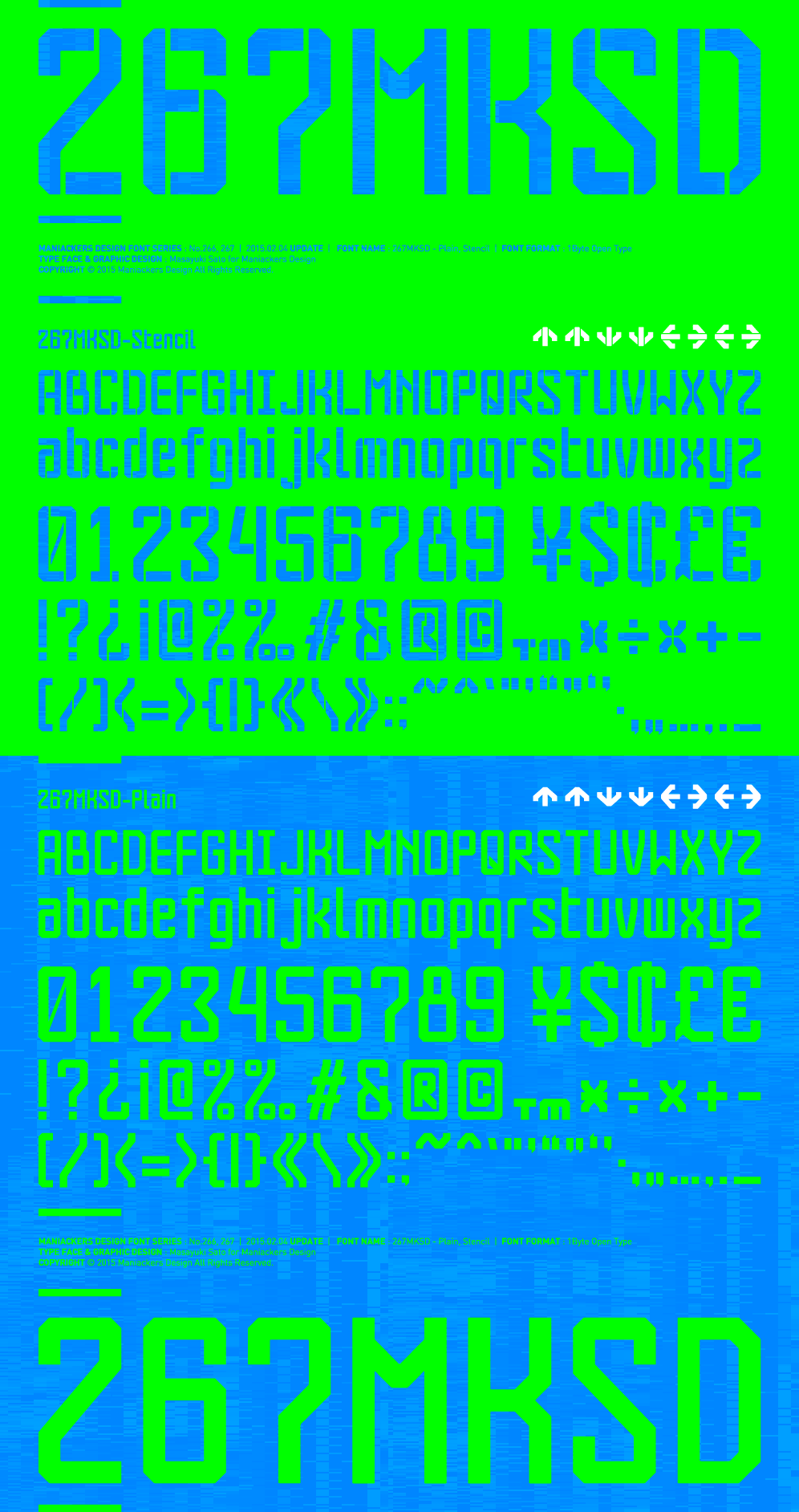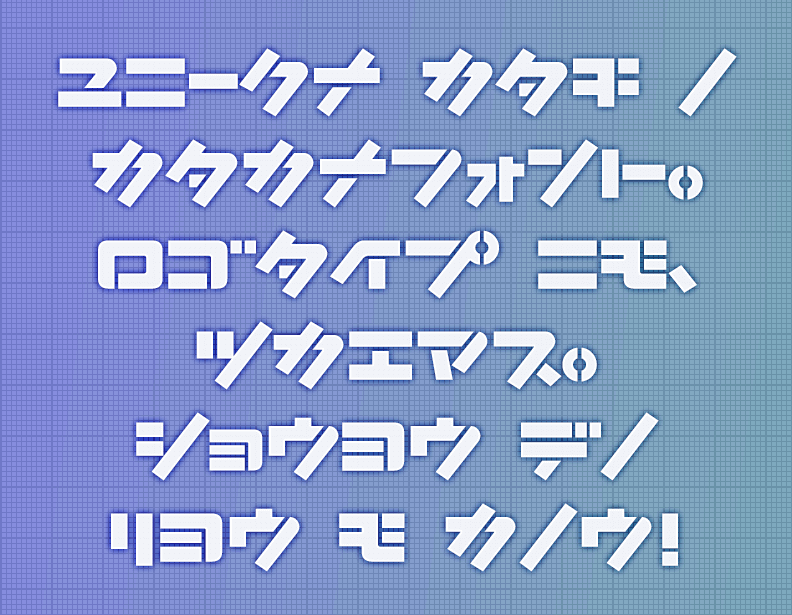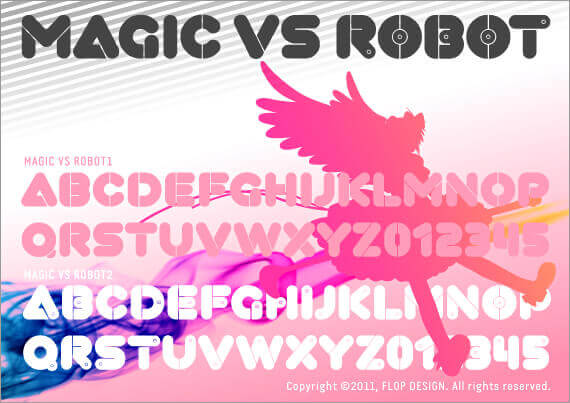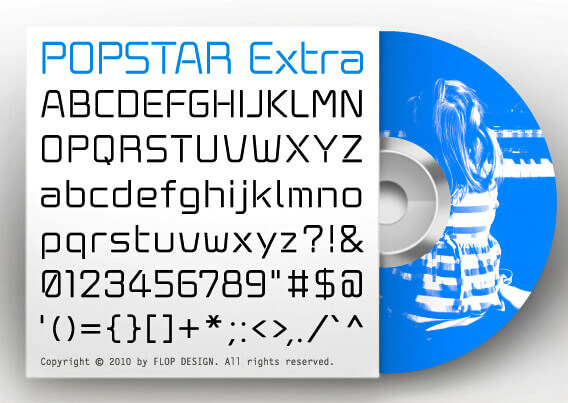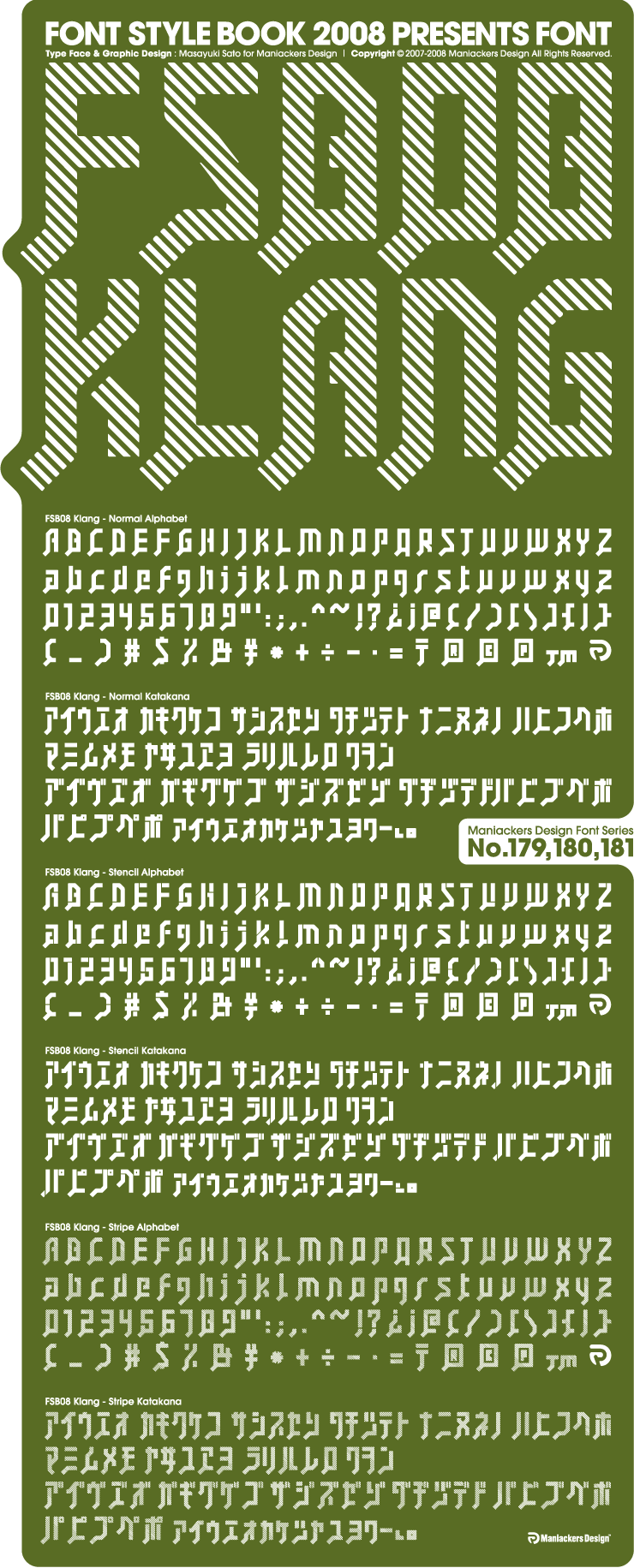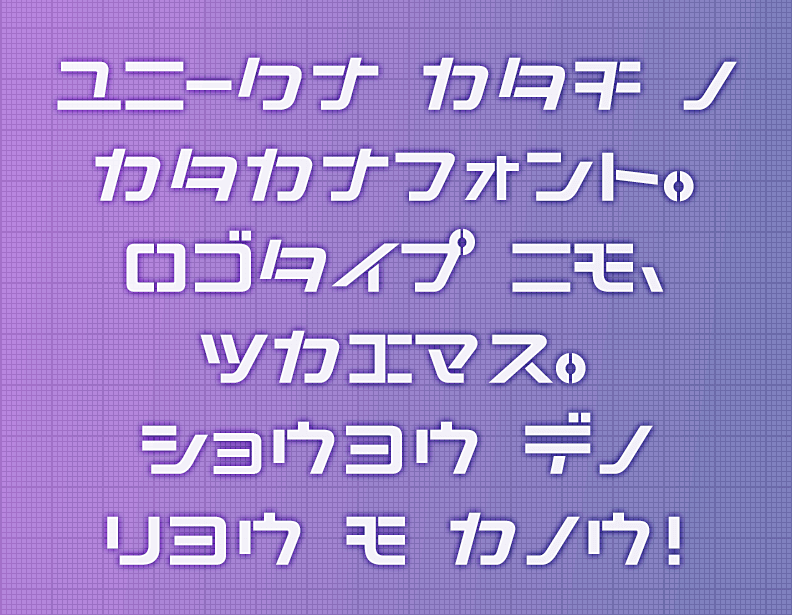
239 Schablone-AL
ステンシルタイプのエクステンド(文字の横幅を広げた)なテクノ系フォント。
267MKSD – Plain, Stencil
Plain(プレーン)とStencil(ステンシル)の2ファミリーが用意されているフォント。
268MKSD Fishhook – Light
「釣り針」のような造形をしたライトな欧文フォント。
Cardia Bold
斜体のステンシル系フォントの太字版。
FSB08 Klang-AL, KT
建築事務所「KLANG」のロゴタイプデザインから派生されたフォント。
Subway
地下鉄をモチーフにした、ちょっとレトロなフォント。
TM Extended-AL
ラウンドタイプのフォント。ステンシルとノーマルの2タイプが用意されています。
Tokaku Stencil
M+フォントの等角アルファベットをステンシルアレンジしたフォント。
ステンシル・カラクレナイ
おしゃれな緩やかなカーブのはらいを特徴としたフォント。
ステンシル・クールボックス
インパクトある太さと均一な線の角度が特徴のフォント。
ステンシル・タワー
がっちりとした安定感があり、文字組の上下が揃っているフォント。
ステンシル・ロジマル
均一な太さの線と角丸のゴシック系フォント。
フロントラインフォント
大胆にデザインされたステンシルフォント。
ポップスターエクストラ
スタンダードで使いやすいスタイリッシュなフォント。
ポップスターネクスト
スタンダードで使いやすいスタイリッシュなフォント。
マジックvsロボット
「魔法文明と機械文明のバトル」をテーマに作られたフォント。魔法物っぽい要素とロボット物っぽい要素が混在するロゴ向けのポップな書体。